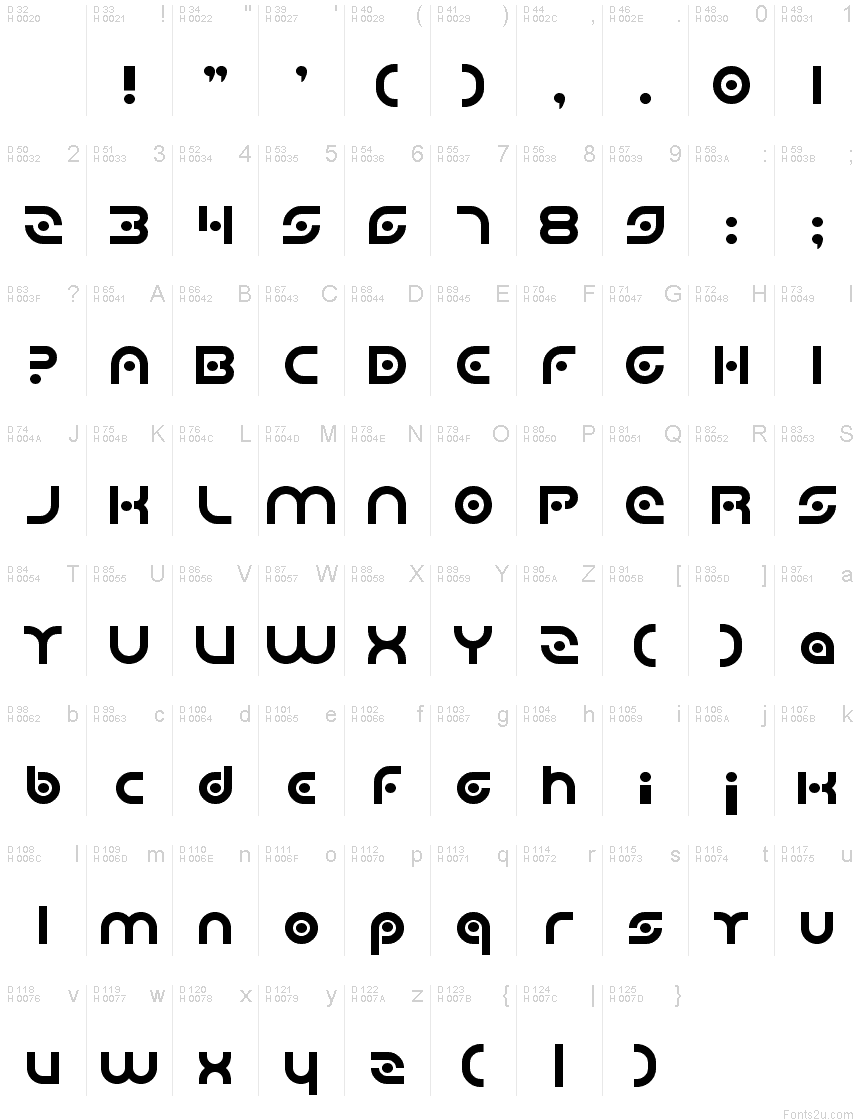
Planetary Orbiter, stworzony przez ShyWedge, to darmowy, futurystyczny krój display o masywnym, kosmicznym klimacie. Litery opierają się na zaokrąglonych, orbitalnych formach i wciętych, kolistych detalach, nadając alfabetowi retro-futurystyczny charakter w stylu zabawkowych robotów, który bardziej kojarzy się z grafiką ekranową lat 90. niż z chłodną technologią.
Idealnie pasuje do tytułów na plakatach, logotypów gier, klubowych ulotek, okładek kaset i krótkich nagłówków na stronach internetowych, gdzie darmowy font może wnieść zabawny, kosmiczny motyw, nie stając się przy tym zbyt surowym. Dzięki kompaktowym, niemal emblematycznym kształtom, świetnie sprawdza się również w napisach tytułowych i krótkich elementach brandingowych, które wymagają wyrazistego, syntetycznego wyglądu.
Planetary Orbiter